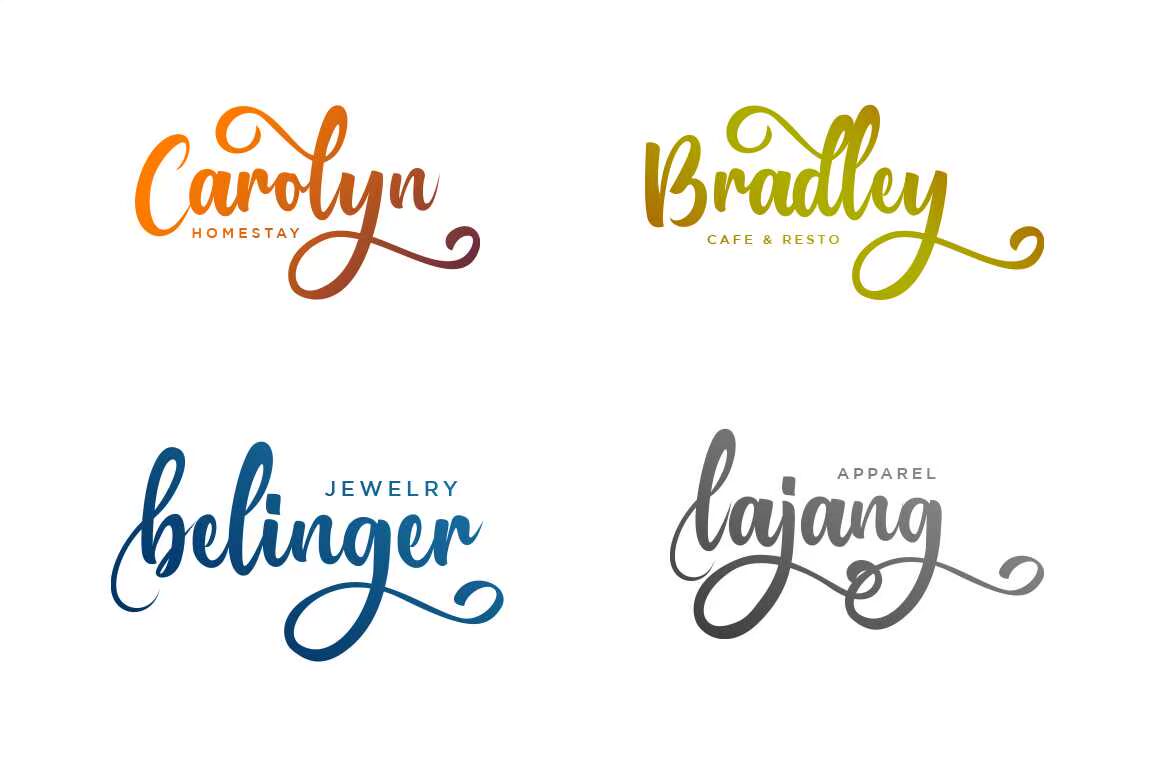
BungalowScriptFont,BeautifulModernCaligraphyFont。支持国际语言,具有BeautifulListicAlternateEasy和Install,适用于您的每个项目,如WeddingInvitation徽标、名片BungalowScriptFont,BeautifulModernCaligraphyFont。支持国际语言,具有BeautifulListicAlternateEasy和Install,适用于您的所有项目,如婚礼活动徽标、名片